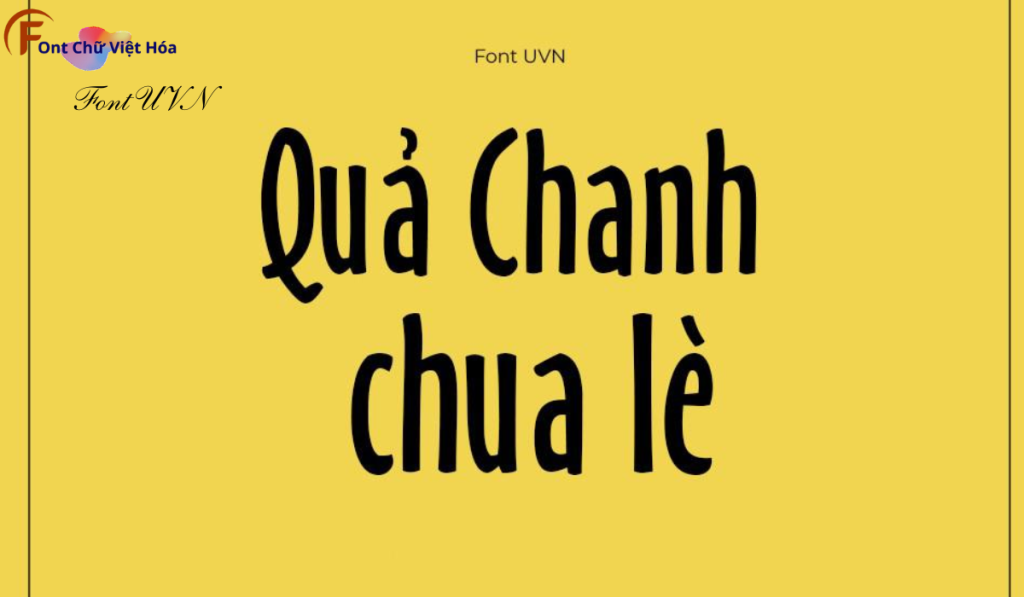
Font UVN Bàn Tay Việt Hóa
Tác giả: UVN Bàn Tay
Bộ Font: UVN
Phân loại: Viết tay, nghệ thuật
Kiểu chữ: Có chân
Độ dày: Thường
Font UVN Bàn Tay Việt Hóa là một font chữ viết tay cá tính, thuộc bộ font UVN. Được thiết kế với mục tiêu mang lại sự mềm mại và thanh thoát, font này lý tưởng cho các dự án thiết kế như thiệp mời, logo, và bao bì sản phẩm. Với các nét chữ uyển chuyển và độ dày đều đặn, Font UVN Bàn Tay Việt Hóa không chỉ dễ đọc mà còn tạo cảm giác thân thiện và gần gũi.